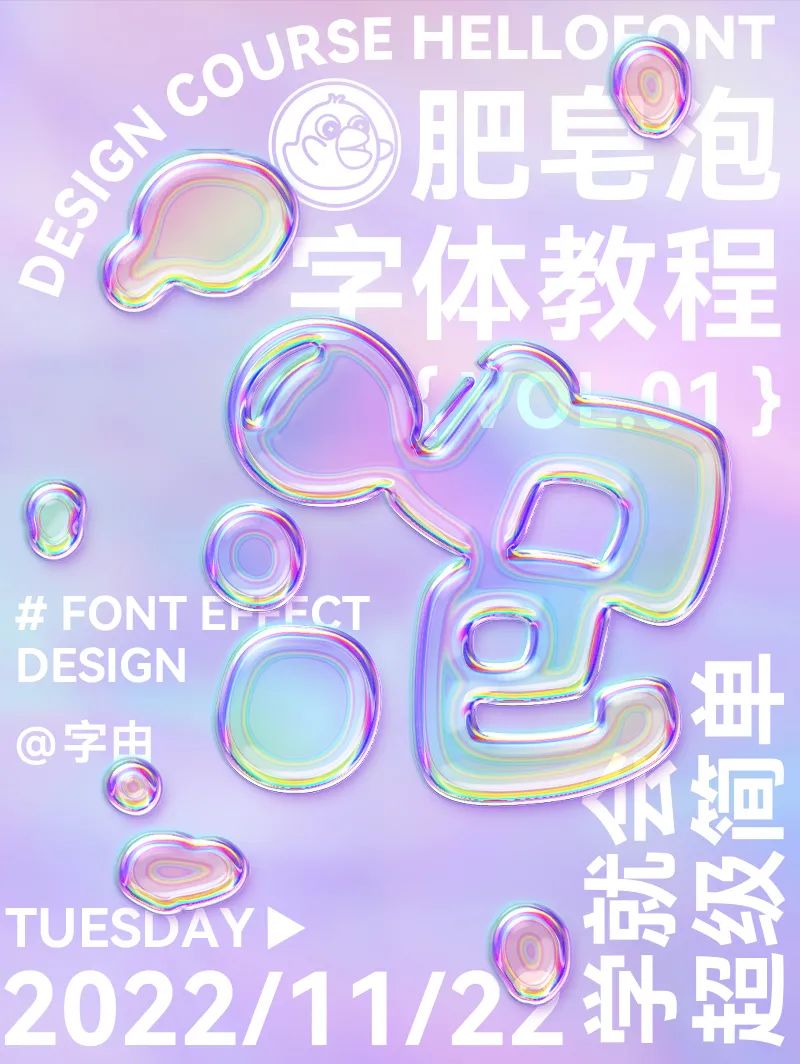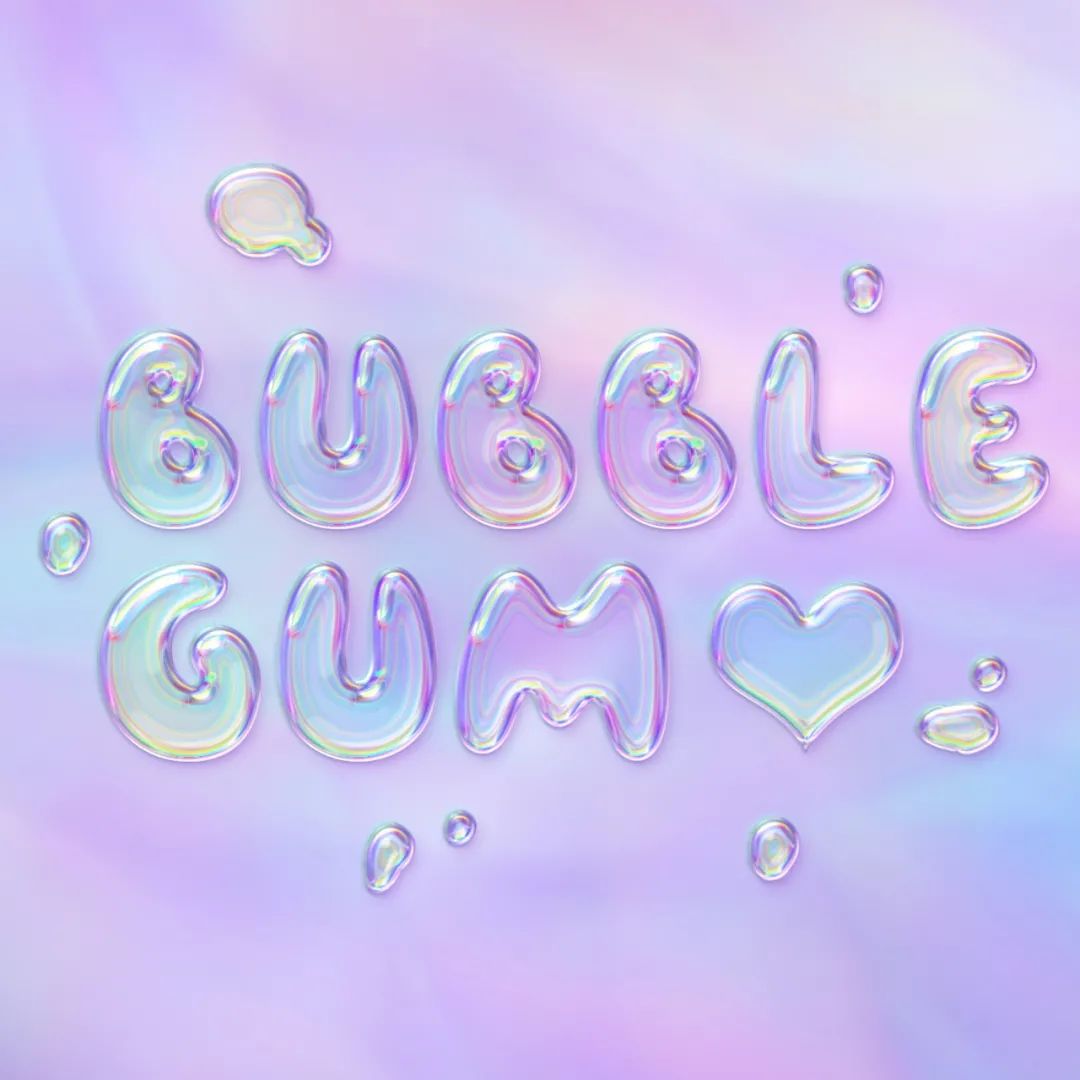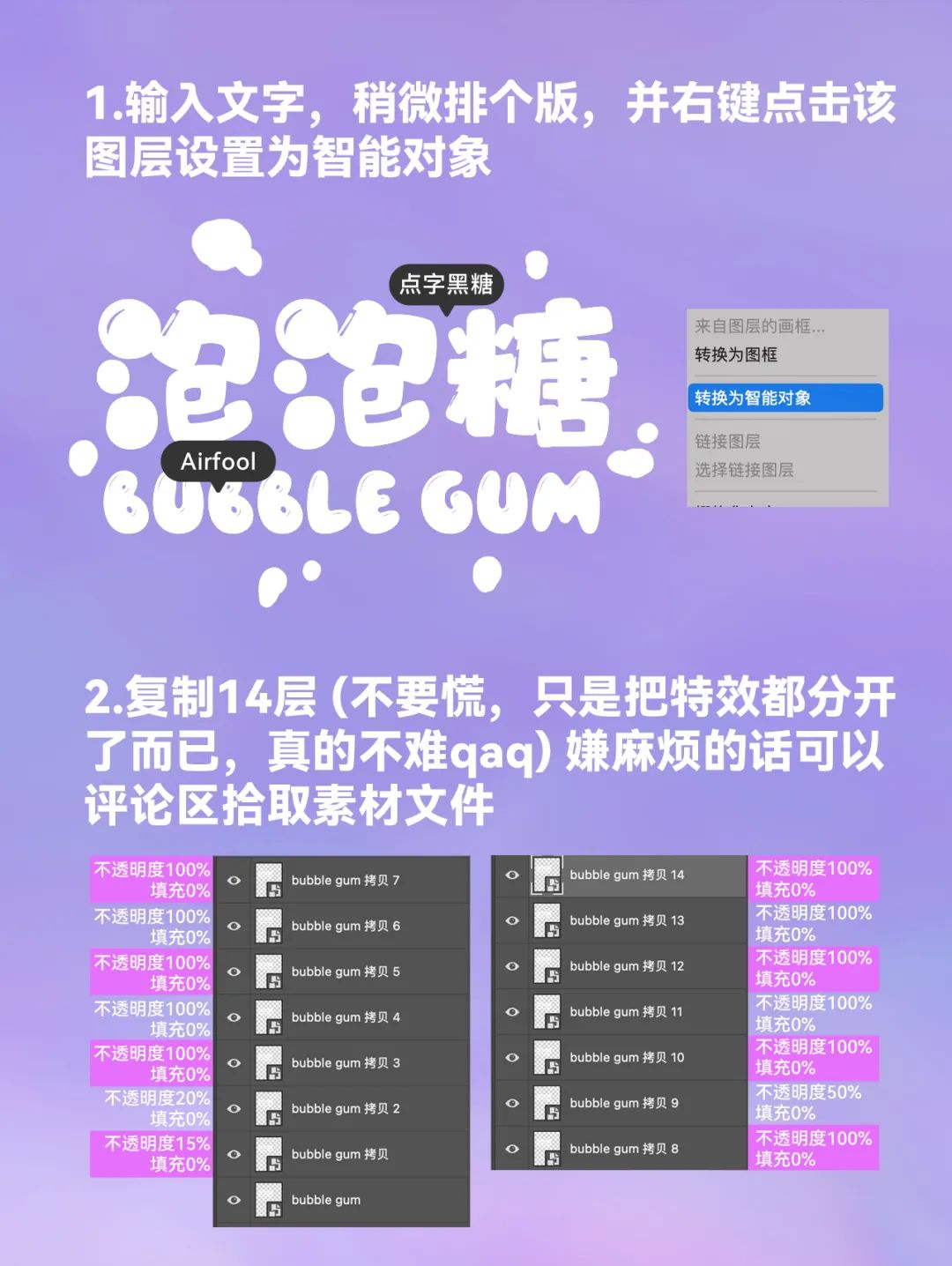
肥美字体的ps专属教程来啦!
哦,不对,放成馄饨皮了,不过看了今天的教程,你会觉得我们的字体有亿点点可爱
不知道小伙伴们有没有遇到过这种情况,精心给海报排了个版,但总觉得还缺点东西?
加了个背景,感觉缺的更多了……
其实这时候往往只需要一些能让画面动起来的细节。
哇,这个肥皂泡看起来很好rua的样子,换成英文一样如梦似幻~
想立即拥有这童话般的字体特效嘛,可以直接下拉到底部,不过你也可以浅学一下~
14层已盖好,顺便请出今天的字体明星!